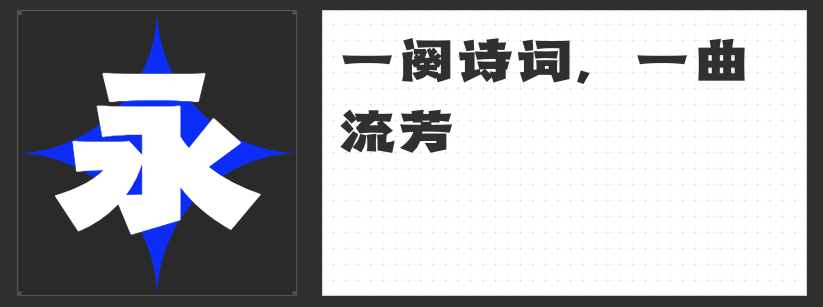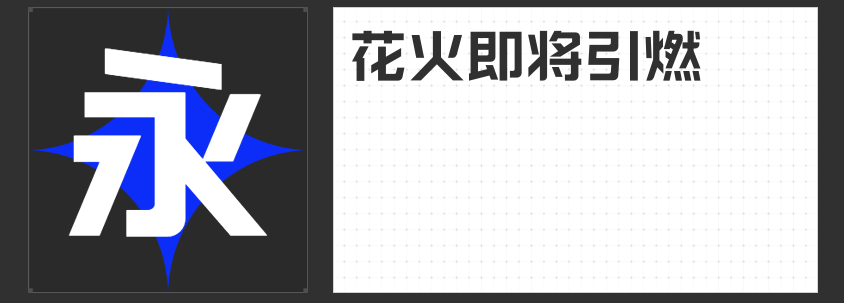
八一建军节字体设计推荐:致敬铁血军魂
在庆祝八一建军节这一庄重而神圣的节日时,选择合适的字体设计能够为相关宣传和活动增添不少氛围与情感。以下是一些精选的字体推荐,希望能为设计师们提供灵感。
造字侠热辣隶简:此字体融合了隶书的古朴与现代设计感,笔划粗犷而不失细腻,如同军人刚毅外表下藏着的柔情与热血。在八一建军节的海报或横幅上,使用造字侠热辣隶简书写“铁血铸军魂”,既能彰显军人的英勇,又能传达出对国家的深情厚谊。
万人字造踏歌行体:这款字体带有一种行云流水般的洒脱与豪迈,仿佛战士们踏着战歌前行的步伐。在纪念活动中,以万人字造踏歌行体呈现“勇往直前”,不仅展现了军人的无畏精神,也寓意着国家的繁荣与昌盛。
励字勇敢黑简 大黑:此字体以其粗犷有力的线条和鲜明的黑白对比,完美诠释了“勇敢”二字。在八一建军节的宣传设计中,选用励字勇敢黑简 大黑作相关设计,能够强烈地表达出对军人牺牲与奉献的崇高敬意,同时也传递出积极向上的正能量。
励字暴风简 超级黑:这款字体如同其名,拥有暴风骤雨般的冲击力,超级黑的字重更是加深了这种力量感。在展现军队力量或庆祝胜利的场景中,励字暴风简 超级黑的“军威震四方”等字样,将让观者感受到强烈的震撼与自豪。
综上所述,这四款字体各具特色,无论是古朴与现代的交融,还是豪迈与力量的展现,都能为八一建军节的设计增添独特的韵味与情感。选择适合的字体,让设计成为连接过去与未来的桥梁,共同致敬那些守护国家的铁血军魂。